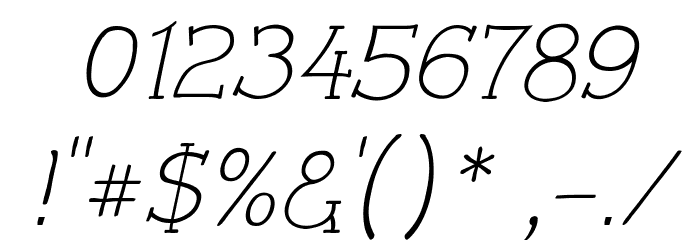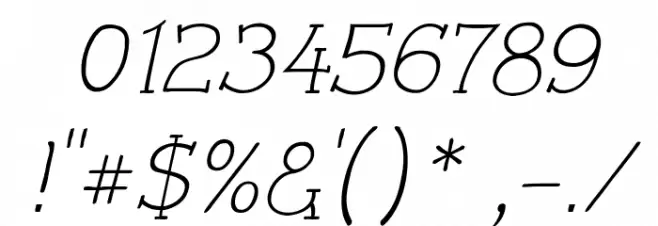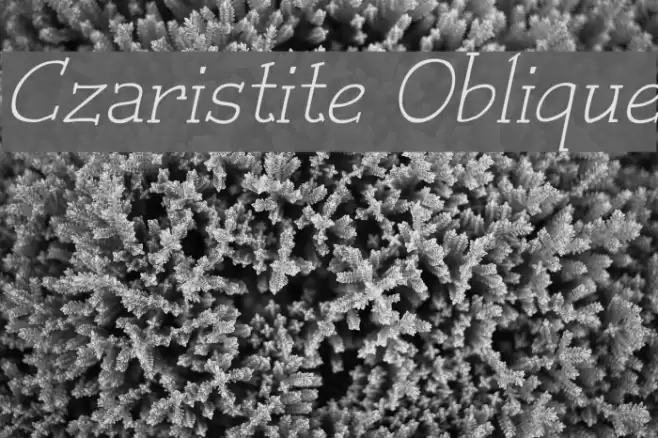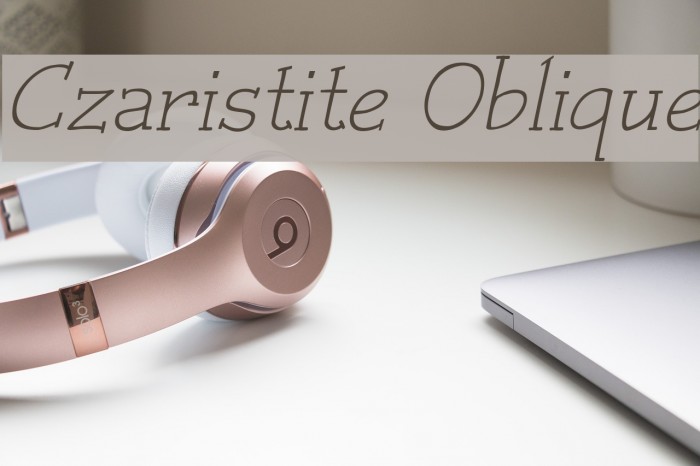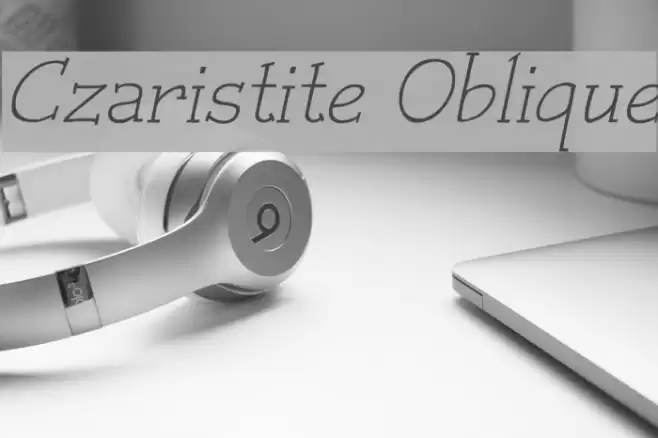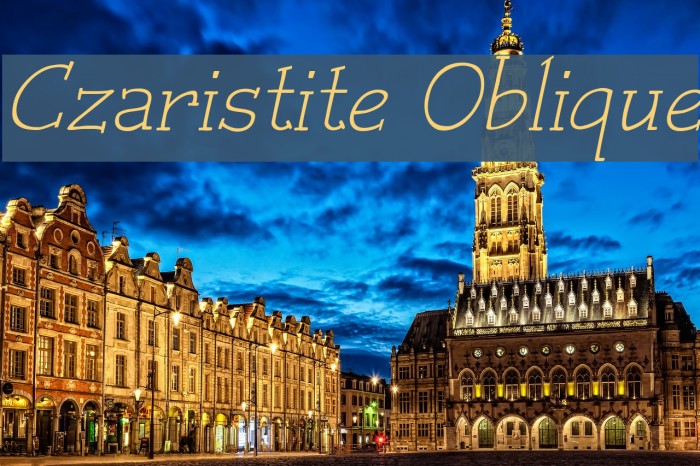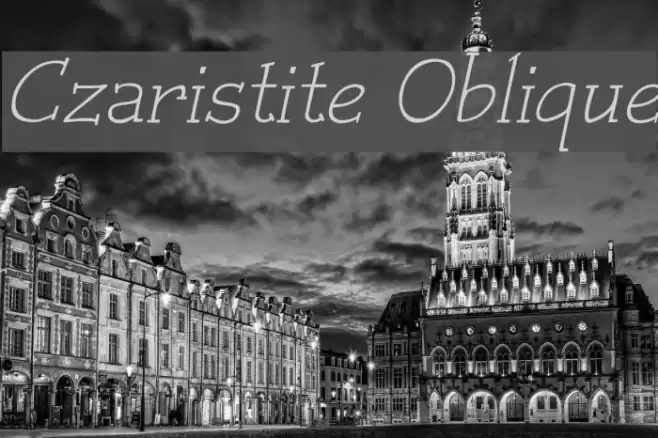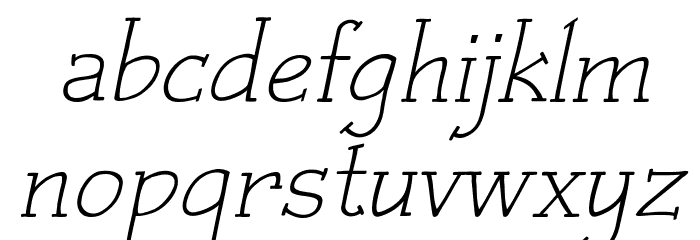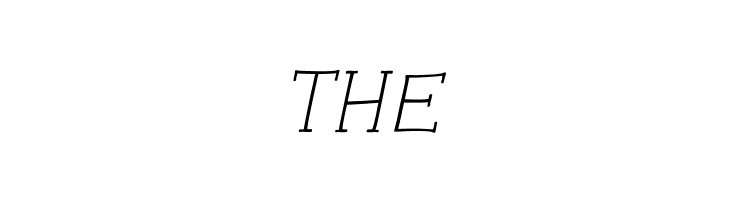
Czaristite Oblique Font
Fonts by Graham Meade - GemFonts
| Nome | Czaristite Oblique |
| Peso | Medium Italic |
| Caso d'uso | Logos, Invitations, Editorial design |
| Progetti proposti | Ideal for wedding invitations, luxury brand logos, elegant packaging, and high-end editorial design. |
| Autore | Fonts by Graham Meade - GemFonts |